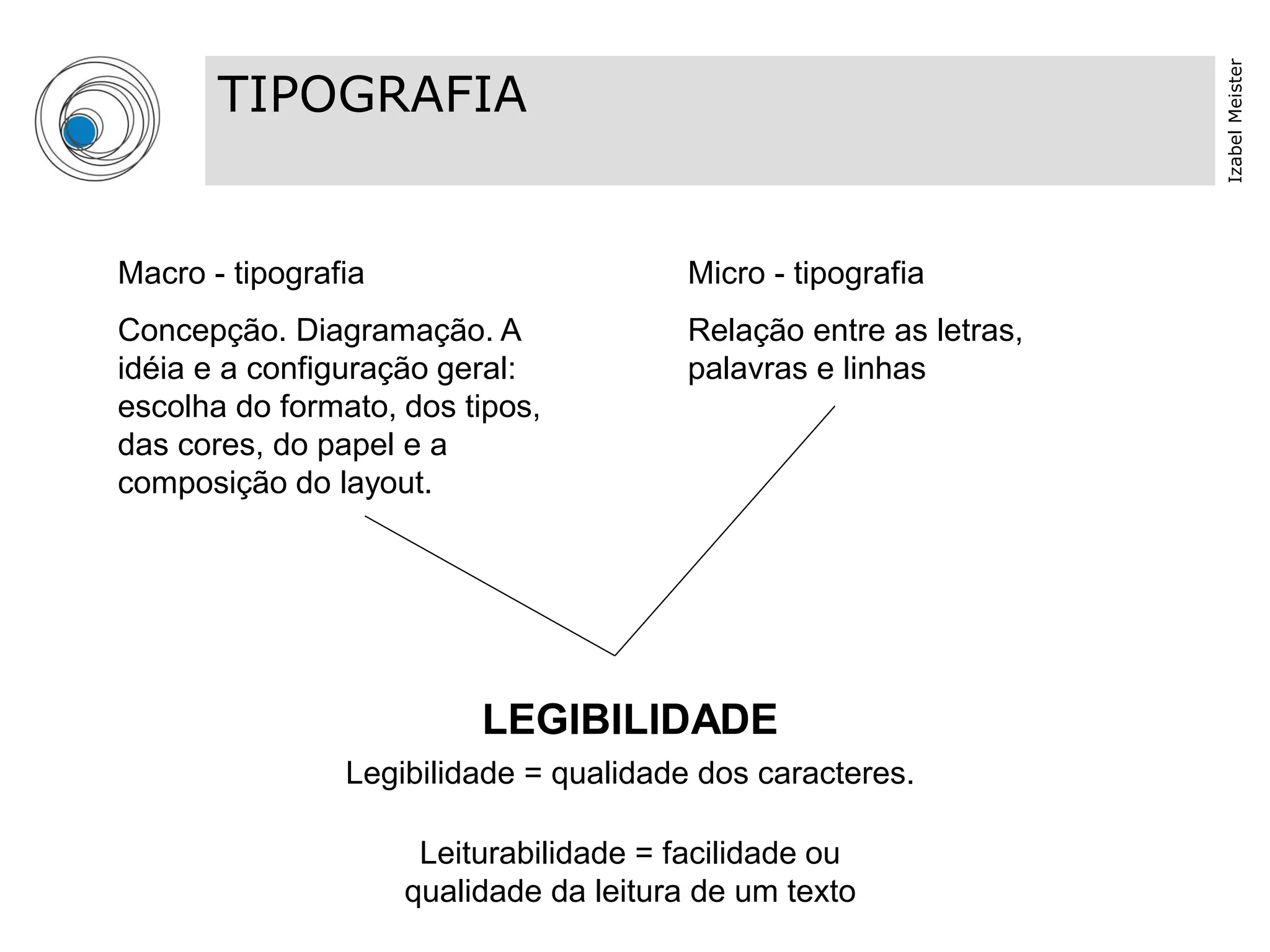
TIPOGRAFIA
Macro - tipografia                       Micro - tipografia
Concepção. Diagramação. A                Relação entre as letras,
idéia e a configuração geral:            palavras e linhas
escolha do formato, dos tipos,
das cores, do papel e a
composição do layout.
LEGIBILIDADE
Legibilidade = qualidade dos caracteres.
Leiturabilidade = facilidade ou
qualidade da leitura de um texto
TIPOGRAFIA
Quem lerá isto?
Como isto deve ser lido?
Quais os meios tipográficos adequados ao
caso?
Como estes meios são adequados de
forma correta?
TIPOGRAFIA
•homem percebe a forma dos objetos devido a luz
refletida ou emitida por eles
•homem ocidental lê da esquerda para a direita e
de cima para baixo
•os olhos varrem o topo das letras
•o movimento dos olhos acontece através de pulos
ao longo da linha, com pausas em intervalos
regulares
•as palavras são percebidas e reconhecidas em
grupo pelas suas formas, lemos letra por letra
quando a palavra é desconhecida
TIPOGRAFIA
FATORES RELATIVOS A FONTE
dimensão / configuração/ contraste/ cor
FATORES RELATIVOS AO OBSERVADOR
familiaridade com desenhos de caracteres/
ângulo de visão/ distância/ tempo de exposição/
movimento
FATORES RELATIVOS AO AMBIENTE
luminosidade/ dimensão
vamos pensar?
mais experiente o leitor maiores são os saltos na linha de texto.
Podemos pensar então que quanto mais semelhantes forem as
formas das letras com os arquétipos das mesmas mais eficientes
serão?
tipografia
Lemos a metade superior dos caracteres com mais facilidade do
que a metade inferior. Caixa baixa apresenta um outline mais
irregular que palavras escritas em CAIXA ALTA proporcionando um
reconhecimento mais fácil.
tipografia                     TIPOGRAFIA
vamos pensar?
Serifas – de maneira geral proporcionam leitura horizontal mais
fluida, maior legibilidade para leituras de grande volume.
As tipografias para sinalização com alta legibilidade, compreensão
da forma e rapidez de leitura pelo equilíbrio entre as proporções dos
traços e a abertura do olho tipográfico = funcionalidade. Isto implica
em claridade e ausência de adornos, sempre? O trabalho está
sempre relacionado ao contexto.
Normal x negrito – massas grandes de texto em negrito podem
atrapalhar o conforto da leitura.
Branco x preto
expansão do                                 expansão do
branco                                      branco
por hábito lemos letras pretas sobre branco.
letras brancas sobre fundo preto parecem maiores e mais espessas
pelo efeito na estrutura ocular.
Halos luminosos – áreas brancas de fronteira parecem ser + brancas e + luminosas
dependem de peso e contraste das formas brancas e pretas envolvidas: quanto >
peso da forma negra ou > a diferença entre traços finos e grossos no caractere
mais forte o halo.
Efeito de expansão + halo = irradiação.
os espaços brancos controlam as formas das figuras percebidas
trabalhar o peso visual
TIPOGRAFIA